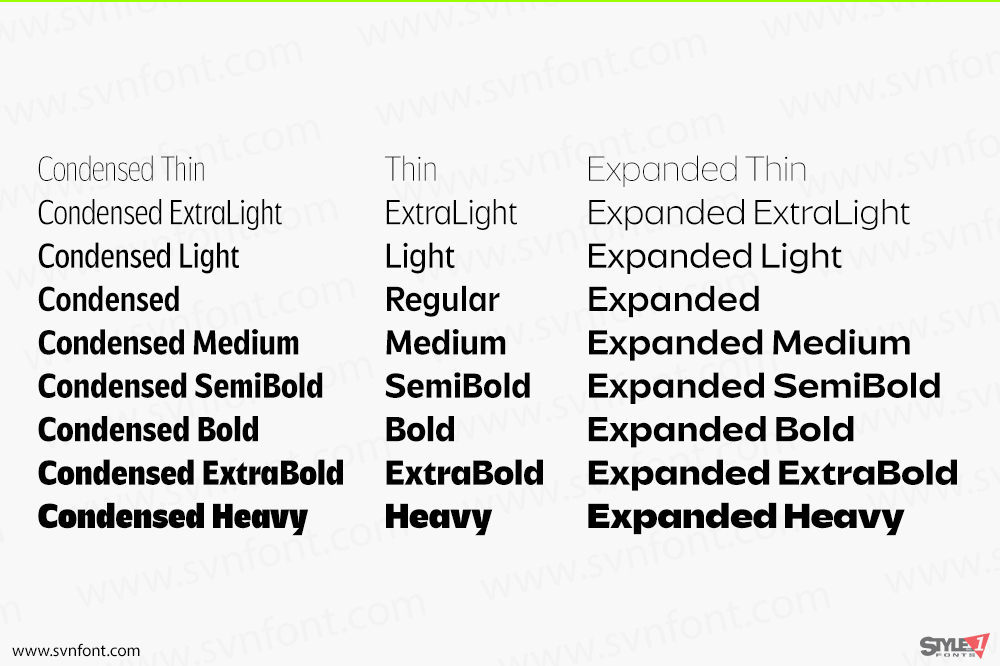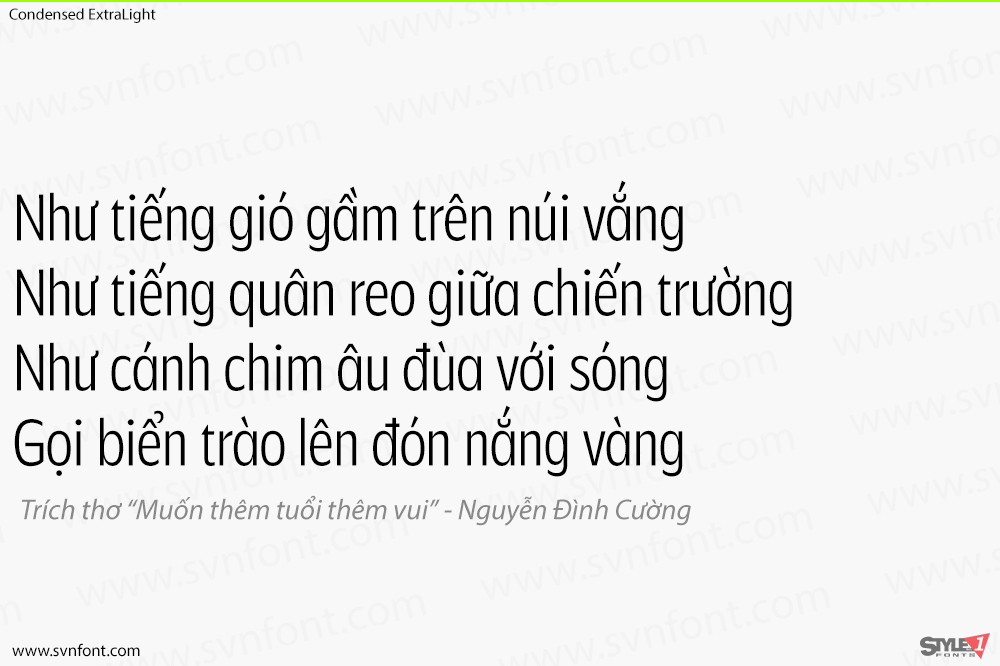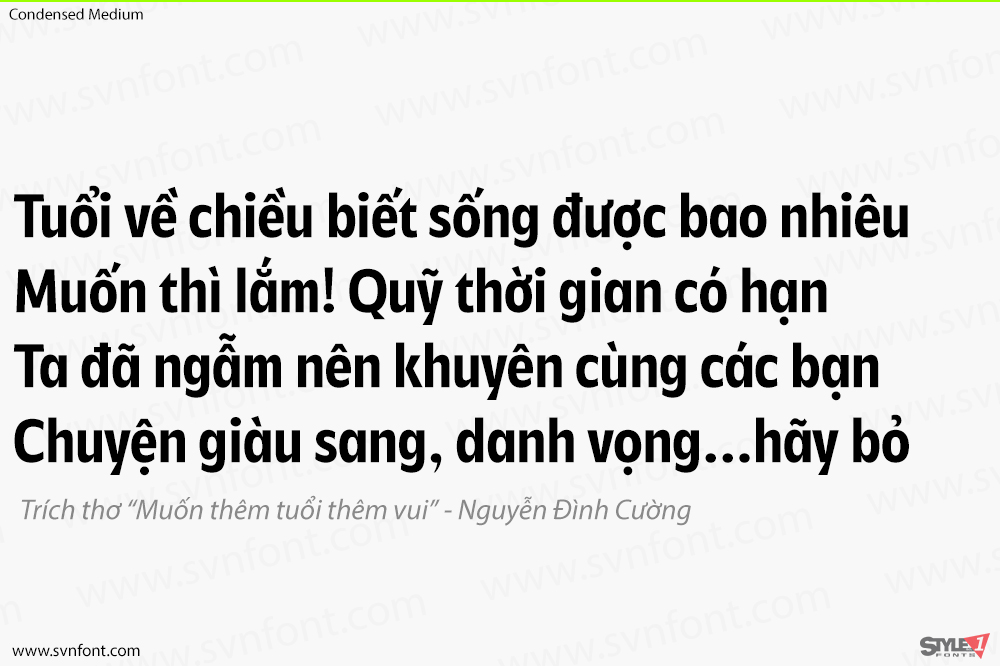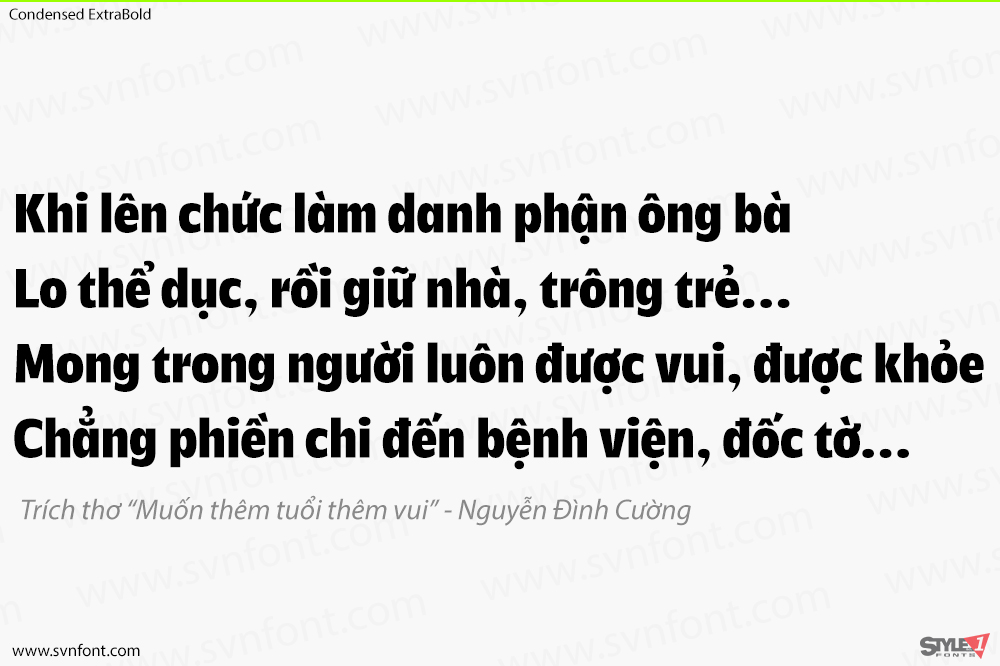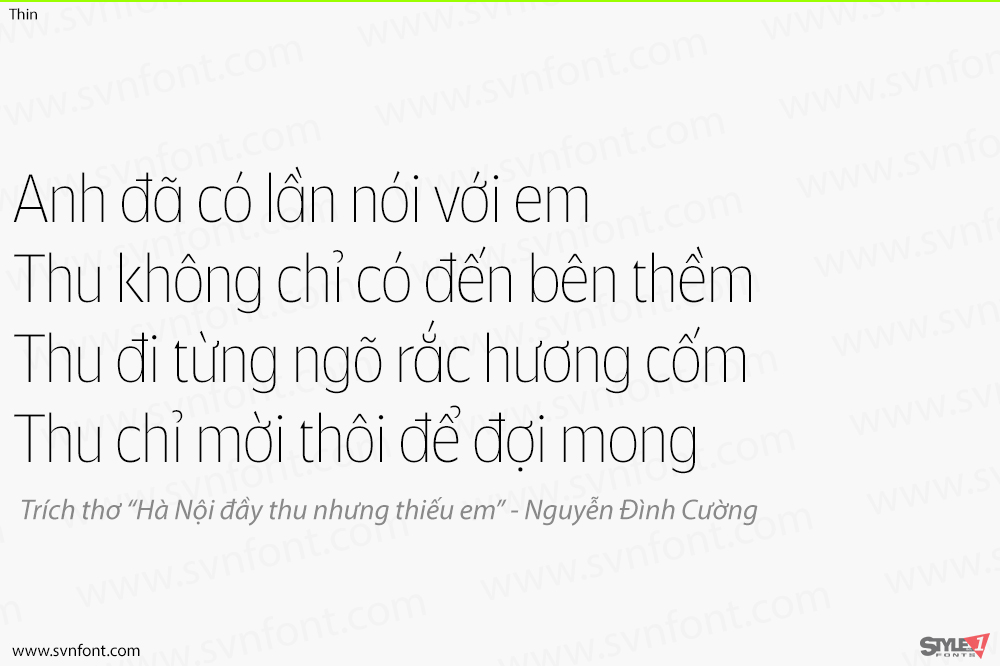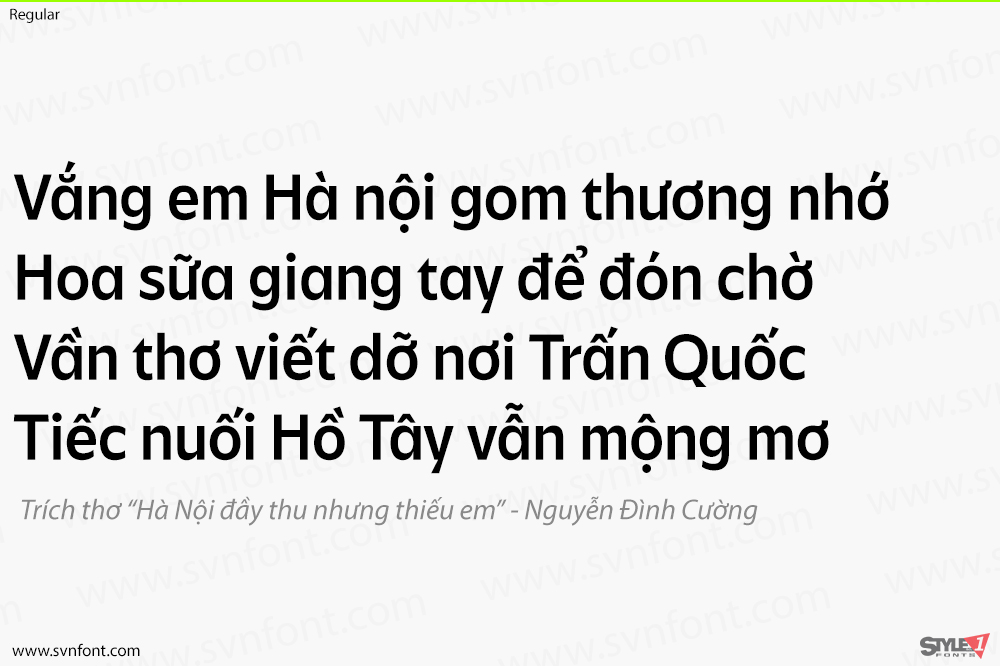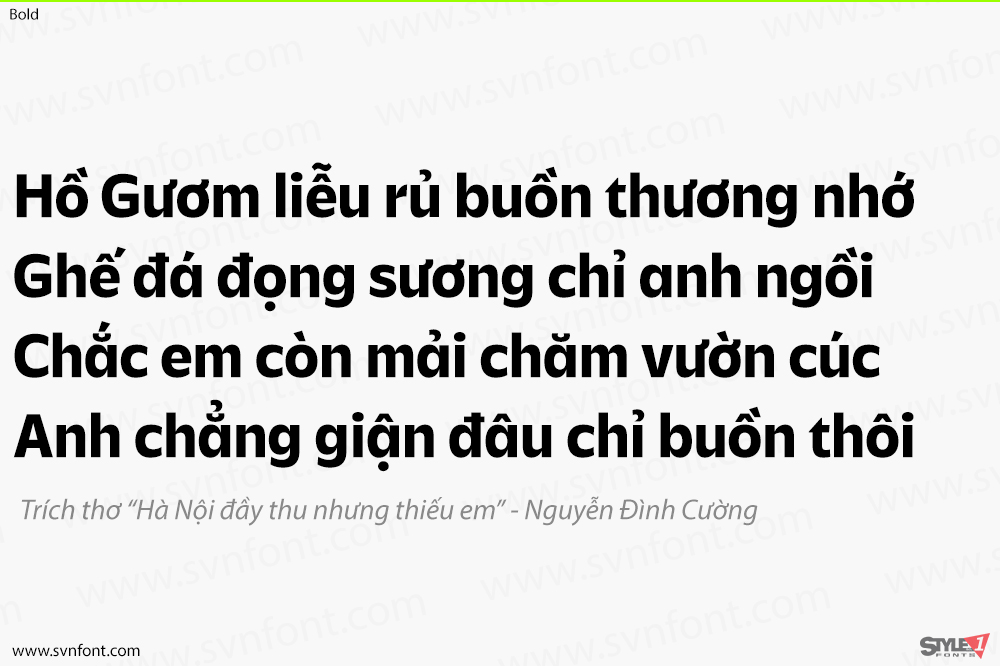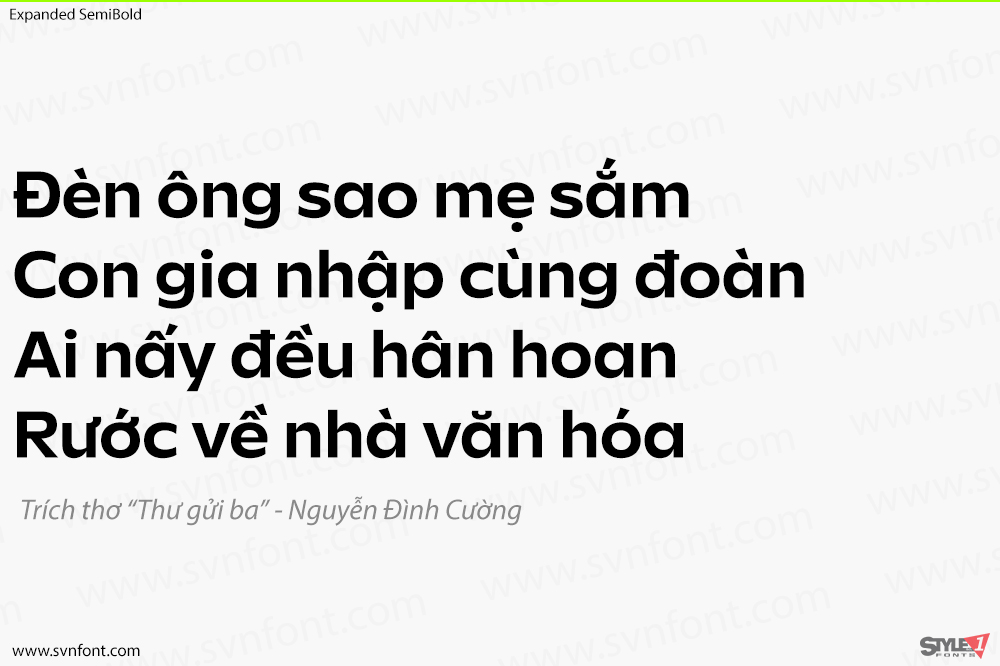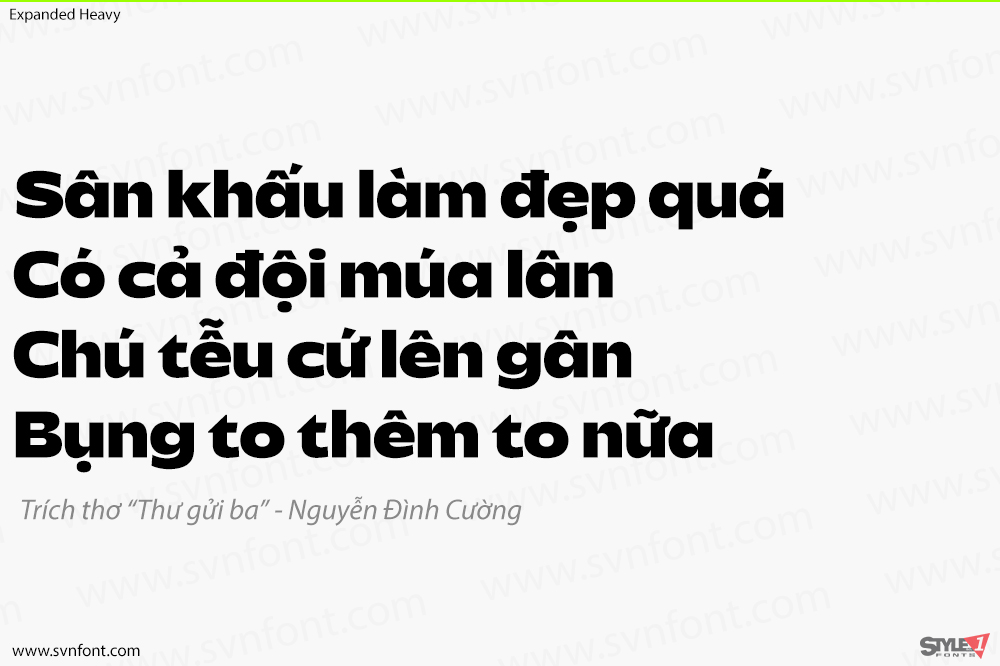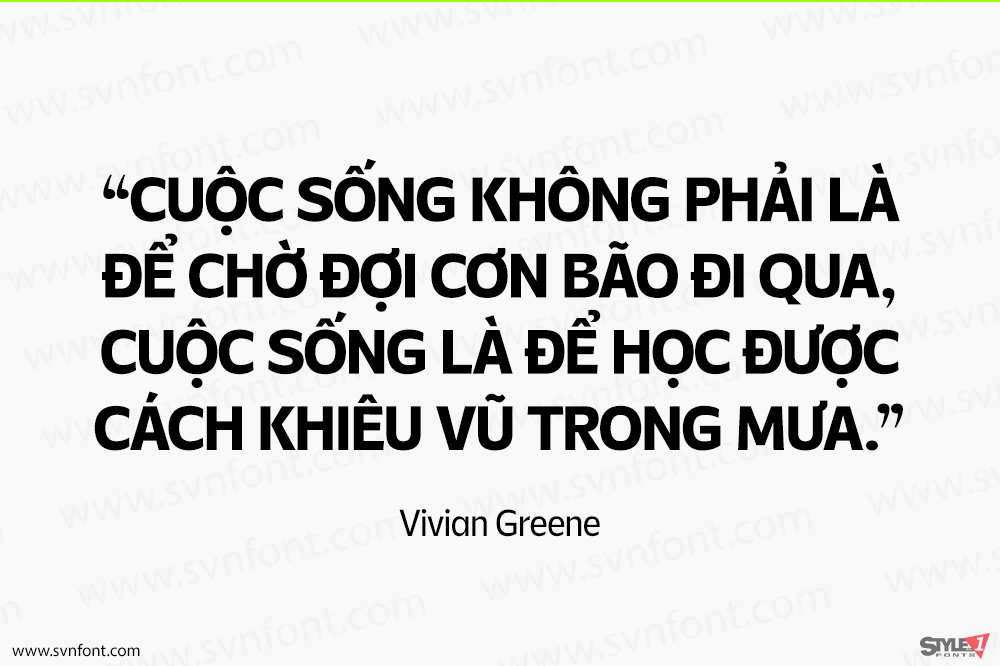
Savior Sans là sự hợp tác thứ ba giữa Sudtipos và Vástago, đây là một kiểu chữ 9 độ dày với 3 chiều rộng khác nhau: condensed (thu hẹp), regular (thông thường) và expanded (mở rộng). Thiết kế đơn giản với các hình dạng mở mang lại một kết cấu khác biệt, phù hợp với nhiều mục đích sử dụng khác nhau như thiết kế web, bao bì hoặc xây dựng thương hiệu. Savior Sans mang đến một cái nhìn đương đại về các phông chữ sans truyền thống, duy trì bản sắc trong từng độ dày của nó. Trong phiên bản biến thể, nó cho phép nhiều tùy chọn khi thiết kế, thích ứng với các giải pháp bố cục khác nhau. Chúng tôi hy vọng bạn thích nó và tận dụng tối đa nó.
Nhà thiết kế: Andrés Felipe Ramírez
Nhà phát hành: Sudtipos